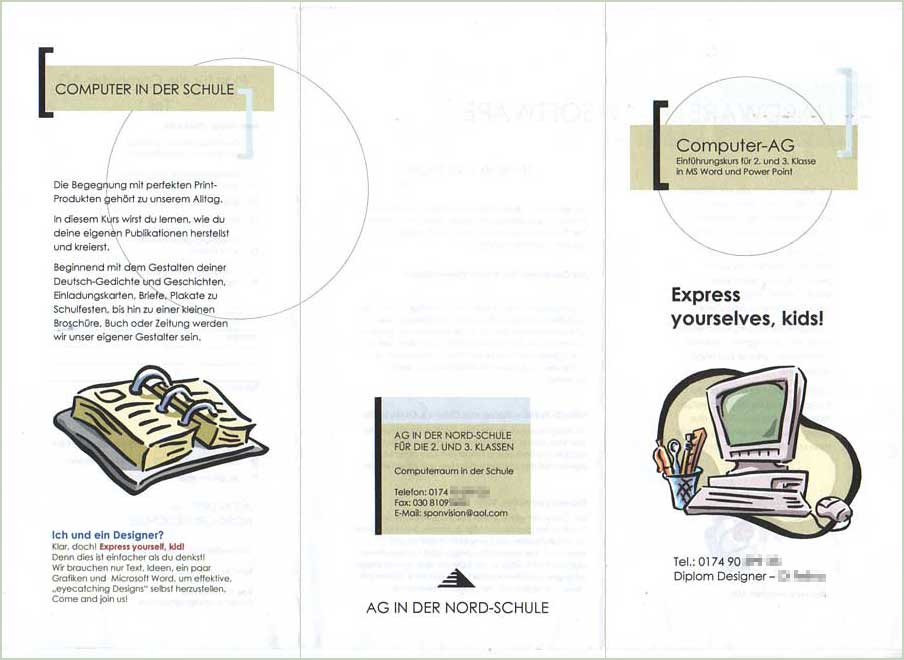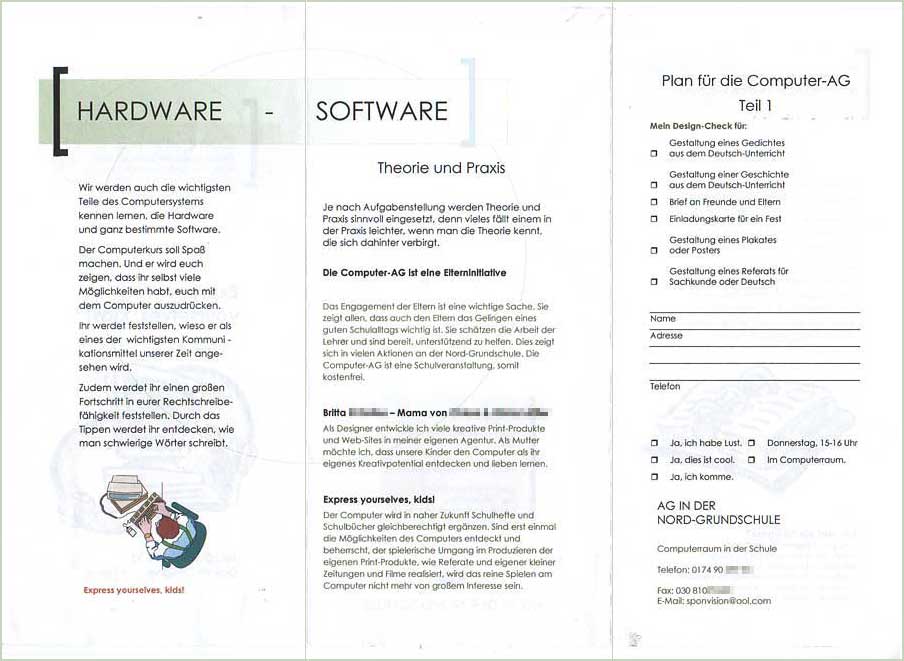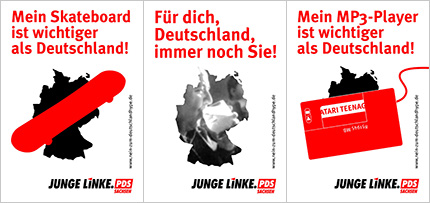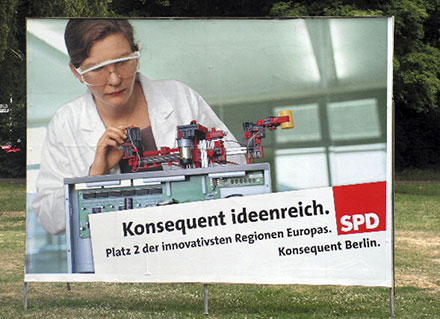
In die Tonne
Lachnummer: Berliner SPD-Wahlplakate
Am 17. September ist Landtagswahl in
Berlin. Klaus Wowereit (SPD) braucht
eigentlich nicht zu tun, um als Regierender
Bürgermeister im Amt zu bleiben: Die Umfragen
bescheinigen seiner Koalition sichere 40 % plus x.
Trotzdem plakatiert die SPD wie immer und wie alle
anderen Parteien auch, nämlich nervig, unausweichlich
und die Wähler für dumm verkaufend. Das zurückgelegte
Geld muss ja schließlich ausgegeben werden.
Die Großplakate der SPD entwickeln sich in der Hauptstadt zur Lachnummer. Auch mich regen sie zum Fantasieren an, wenn ich an ihnen vorbei rausche.
»Wenn ick meine BZ lese, will ick nüch jestört werdn, klar?«
»Dit is jenau mein Humor: Zeitung lesen und den Augenkontakt zur Kundschaft konsequent vermeiden.«
»Hätt’ ich nie gedacht, dass sich die Experimente für die Airbus-Statik zu ein Bruchteil der Kosten mit Fischer-Technik durchführen lassen. Das müssen wir dem Senator für Forschung natürlich nicht auf die Nase binden.«
»Weil mir der Baukasten gestern um die Ohren geflogen ist, muss ich jetzt diese dämliche Schutzbrille tragen.«
Dazu: Die Glosse Wahrheit und Wahlplakate in der Berliner Zeitung und eine Frage im Spreeblick.
»Da, ihr Lieben, liegt Rumänien ... und dort geht es den Kindern viel schlechter als bei und in Berlin.«
»Du, Tante Renate: Wie lange müssen wir in diesem Plattenbau mit den bunten Jalousien noch eingesperrt bleiben?«
»Ich hab’ mich auf der Fanmeile in Klinsi verliebt. Seitdem besucht er mich alle 14 Tage in meiner Dachgeschoss-Wohnung am Kollwitzplatz.«
»Als die Berliner Bank die Finanzierung unserer Eigentumswohnung übernahm, haben wir sofort unser Studium abgebrochen. Inzwischen leben wir ganz gut von den Mieteinnahmen unserer 7 Objekte.«
Die Großplakate der SPD entwickeln sich in der Hauptstadt zur Lachnummer. Auch mich regen sie zum Fantasieren an, wenn ich an ihnen vorbei rausche.
»Wenn ick meine BZ lese, will ick nüch jestört werdn, klar?«
»Dit is jenau mein Humor: Zeitung lesen und den Augenkontakt zur Kundschaft konsequent vermeiden.«
»Hätt’ ich nie gedacht, dass sich die Experimente für die Airbus-Statik zu ein Bruchteil der Kosten mit Fischer-Technik durchführen lassen. Das müssen wir dem Senator für Forschung natürlich nicht auf die Nase binden.«
»Weil mir der Baukasten gestern um die Ohren geflogen ist, muss ich jetzt diese dämliche Schutzbrille tragen.«
Dazu: Die Glosse Wahrheit und Wahlplakate in der Berliner Zeitung und eine Frage im Spreeblick.
»Da, ihr Lieben, liegt Rumänien ... und dort geht es den Kindern viel schlechter als bei und in Berlin.«
»Du, Tante Renate: Wie lange müssen wir in diesem Plattenbau mit den bunten Jalousien noch eingesperrt bleiben?«
»Ich hab’ mich auf der Fanmeile in Klinsi verliebt. Seitdem besucht er mich alle 14 Tage in meiner Dachgeschoss-Wohnung am Kollwitzplatz.«
»Als die Berliner Bank die Finanzierung unserer Eigentumswohnung übernahm, haben wir sofort unser Studium abgebrochen. Inzwischen leben wir ganz gut von den Mieteinnahmen unserer 7 Objekte.«
Linke Erbsen- und Flaggenzähler
Politik kann so ekelhaft sein ... Hilfe, Ich möchte wieder über Fußball schreiben.
Verglichen mit der provinziellen Aktion Nein-zum-Deutschlandhype bewegt sich die Debatte um Merkels Video-Podcast (und ihre Politik) geradezu auf höchstem Streitkultur-Niveau.
Am 19. Juni gaben die Junge Linke.PDS Sachsen und Julia Bonk (MdL) eine Pressemitteilung heraus, in der das »übermässige und im Moment an allen Ecken stattfindende Schwenken der deutschen Flagge heftig kritisiert wird«. Als Reaktion darauf schickte Peter Porsch, Vorsitzender der Linksfraktion im sächsichen Landtag eine Presseerklärung hinterher, in der er sich von Bonks Meinung distanzierte.
Nun macht die Junge Linke mit Aufklebern Jagd auf hedonistische Jugendliche, denen MP3-Player und Skateboard gefälligst wichtiger sein soll »als Deutschland« (gesetzt in FF Meta ... meine Augen sind zutiefst verletzt).
Wenn man die avisierte Zielgruppe mit dieser Bauernfängerei schon nicht erreicht, vielleicht gelingt es ja, die wenigen tausend verbliebenen Jungwähler im Land auch noch in die Politikverdrossenheit zu treiben.
Rote Karte für die WM-Trikot-Ziffern
Man kann über vieles streiten auf der Fußball WM 2006 ... Brasiliens »Ballzauber«, Schiedsrichter-Entscheidungen, die Macht der Fifa ... in einem sind sich die Experten einig: Die Qualität der Trikot-Beschriftungen spottet jeder Beschreibung. Vor allem die Ziffern sind grausam (die brasilianischen mal ausgenommen).
Der holländische Schrift-Experte Sander Neijnens, er beschäftigt sich seit 2000 mit den Schriften auf Fußball-Trikots, schrieb mir: »Ich begreife nicht, dass Designern, die für Nike, Adidas oder Mannschaften wie Real Madrid, Inter Mailand und Chelsea gestalten, nichts besseres einfällt als Bauhaus gequetscht, Industria verzerrt oder martialische Rechteck-Konstruktionen.«
Liebe Leitung der Nord-Schule: Bitte lass diesen Kurs nie stattfinden!
Außenseiten eines Aushangs an der Zehlendorfer Nord-Schule, der für einen Schüler-Computer-Design-Kurs wirbt
Nur eins dürfte an diesem Flyer wahr sein: dass er mit Microsoft Word gestaltet wurde